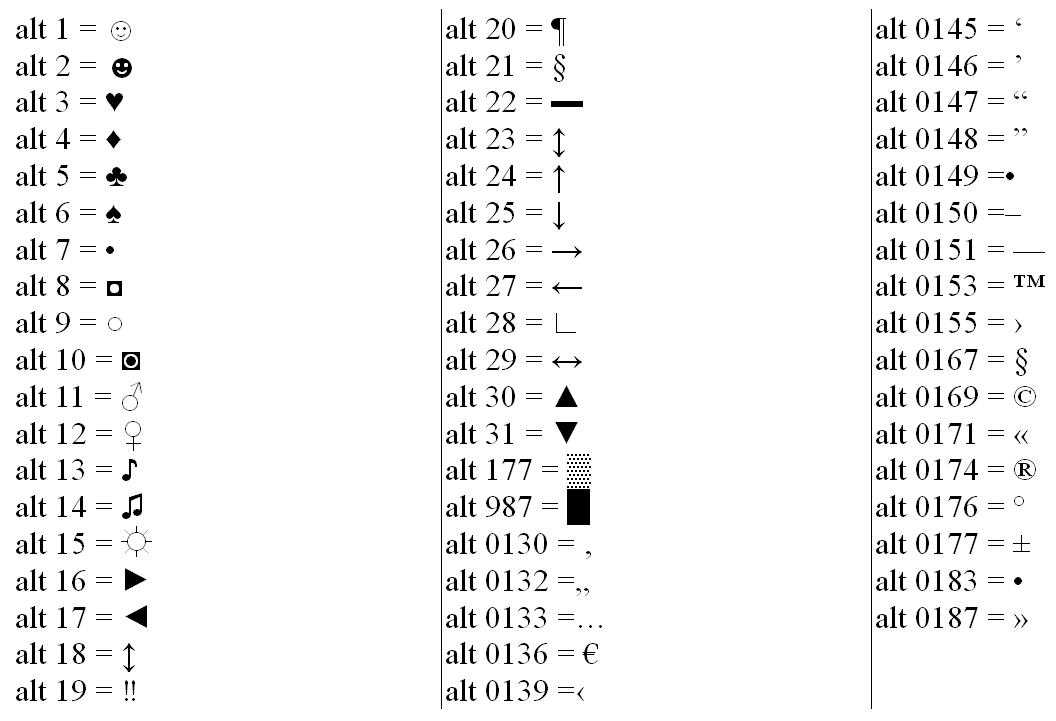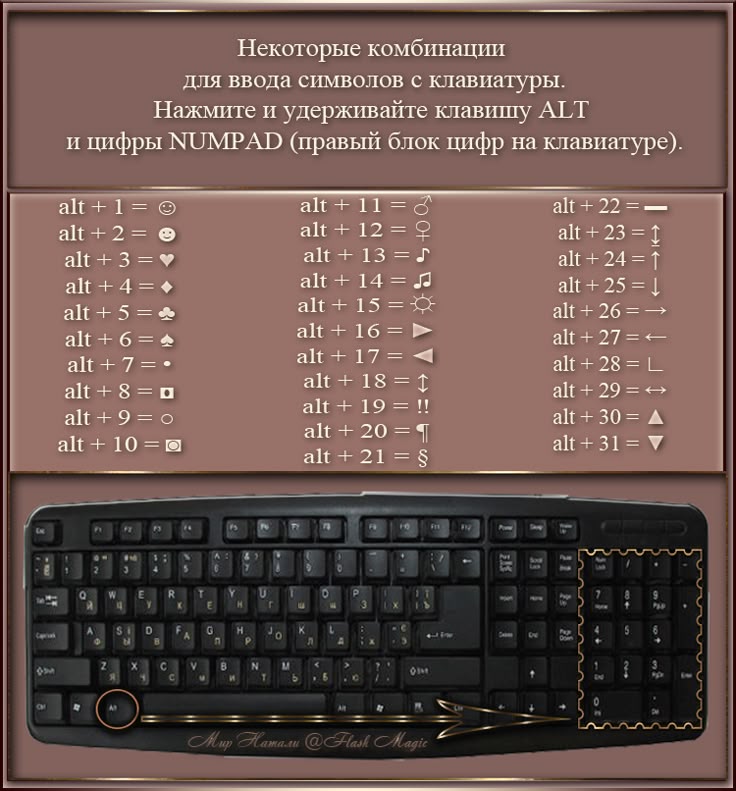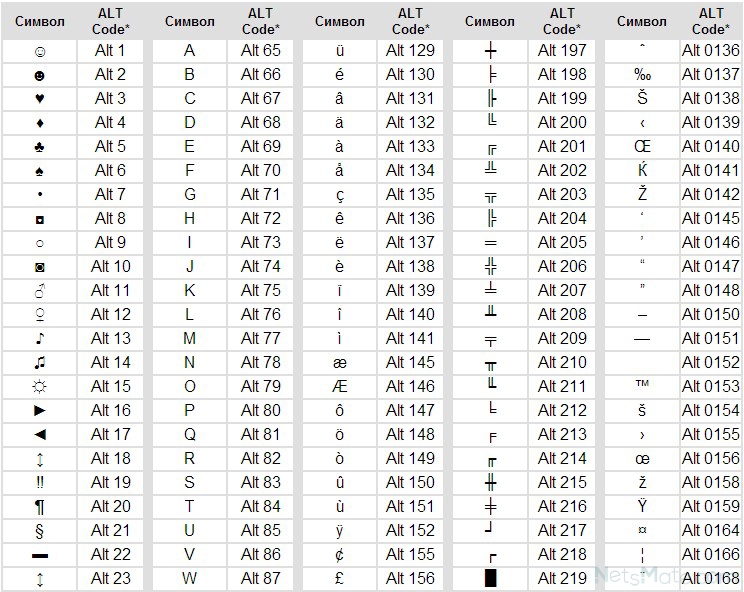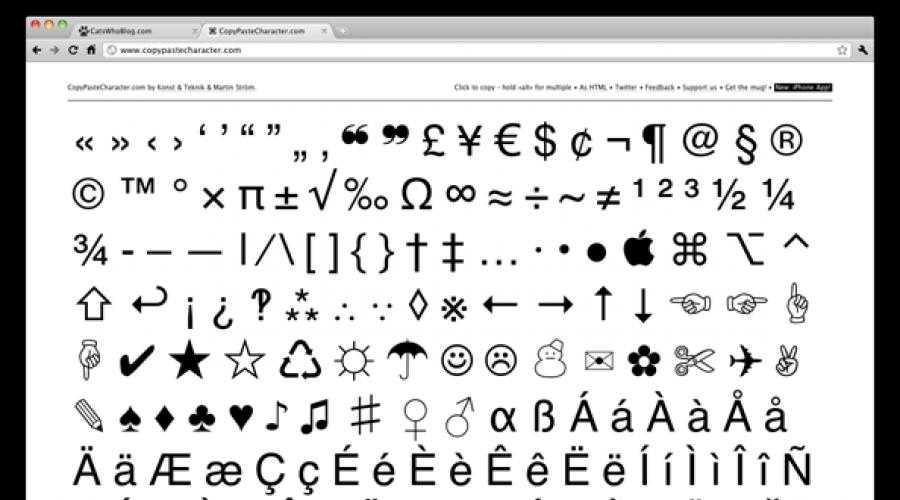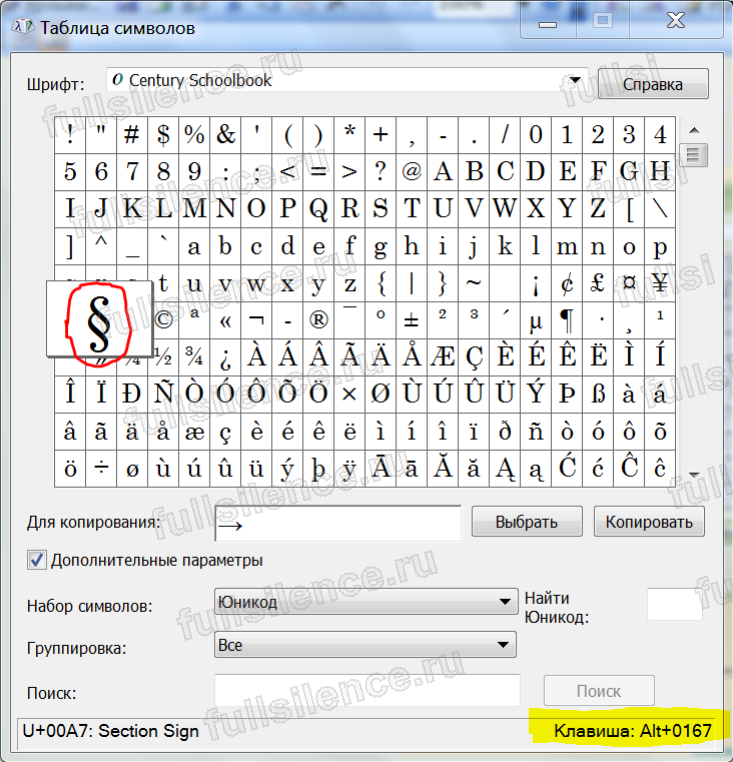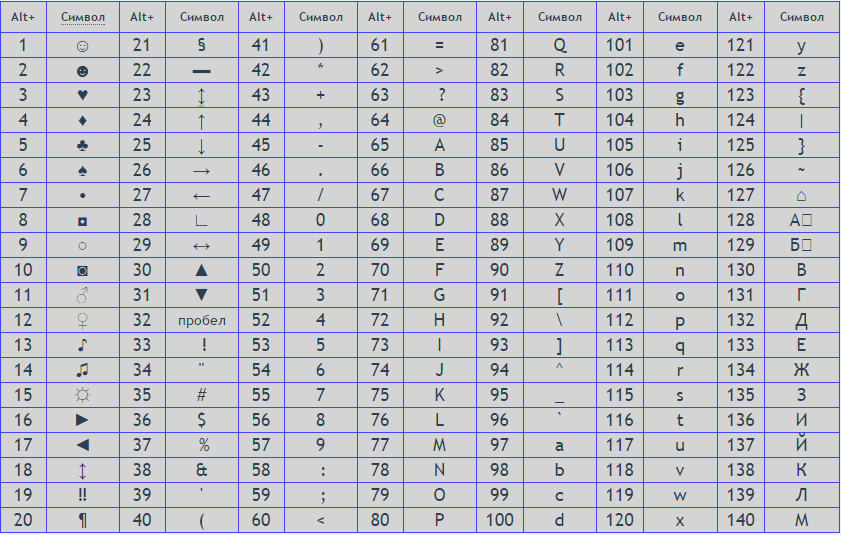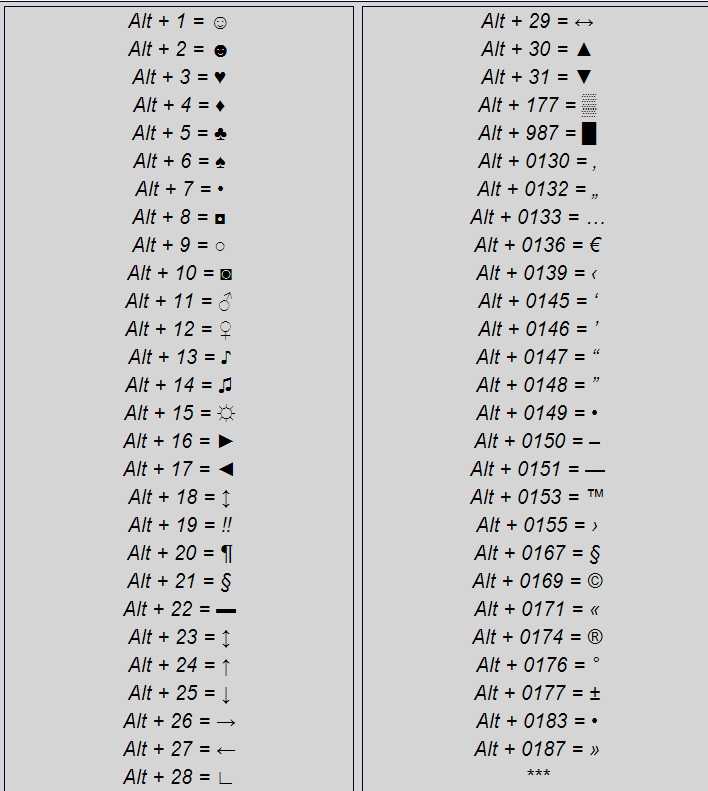
Несколько советов, как написать красивыми буквами слово
Всем известно выражение о том, что красота – страшная сила. И применять ее можно по-разному. В данной статье поговорим о том, как научиться красиво писать слова. Что для этого нужно знать и уметь?
О вариантах
В современном мире нужно уметь не только красиво писать собственной рукой на бумаге, но и интересно преподнести текст в социальных сетях, личном блоге и т. д. Сегодня это весьма важно, т. к. традиционная переписка в большинстве случаев утратила свои позиции, отдав первенство общению при помощи средств интернета.
Рукописный текст: история
В первую очередь все же следует разобраться, как написать красивыми буквами текст вручную. Интересным для многих покажется небольшой экскурс в историю. Как бы это странно ни прозвучало, но развитию письма (именно красивого, каллиграфического) посодействовала Библия. Произошло это примерно в 8-9-м веке, когда монахи Ирландии и Шотландии начали создавать иллюминированные Библии, считающиеся сегодня верхом письменного искусства. Для этого набирались священнослужители, которые обучались красивому ровному письму. И процесс этот, нужно сказать, не так уж быстр: для качественного обучения требовалось много времени и сил.
О каллиграфии
Искусство красиво писать называется каллиграфией. С греческого языка данный термин переводится как «красивый почерк». Интересным окажется и тот факт, что каллиграфия сегодня – это одно из течений в изобразительном искусстве. Большинство мастеров красивого рукописного текста свое умение определяют как оформление надписей в гармоничной, искусной и экспрессивной манере. То есть это не просто красиво написанный текст, но и грамотно и со вкусом вписанный в общую картину.
Что нужно знать?
Итак, что следует предпринять, если хочется разобраться в том, как написать красивыми буквами слово? В первую очередь важно хорошенько проанализировать свой почерк. Рекомендуется предварительно выбрать определенную манеру письма, которая подойдет конкретному человеку в зависимости от того, как он переносит текст на бумагу. На что нужно обратить внимание?
- На то, какие буквы получается украшать автоматически (завитки, дополнительные полоски).
- На наклон почерка.
- На ширину между буквами в одном слове.
В зависимости от этого можно продумать новый, украшенный стиль своего письма.
Что нужно иметь?
Итак, разбираемся далее, как написать красивыми буквами определенный текст. Для этого требуется запастись определенными вспомогательными средствами:
- Пишущим предметом. Это может быть ручка, карандаш, фломастер – не столь важно. Главное, чтобы предмет был удобен для пишущего. Прежде чем приступать к столь важному делу, нужно сделать несколько росчерков на бумаге. Это поможет убедиться в правильности выбора пишущего предмета.
- Самой бумагой. Она должна быть подходящей. Так, на лоснящемся листе маркер или фломастер рискует размазаться, а карандаш и вовсе откажется писать. Это нужно учитывать.
Правила красивого написания
Изучаем далее материал, который подскажет, как написать красивыми буквами нужный текст. Для достижения поставленной цели нужно соблюсти несколько простых правил. Что же делать?
- Тренироваться. Чтобы текст получился ровным и красивым, нужно немного попрактиковаться. Предварительно можно попробовать несколько разных манер письма и выбрать ту, которая больше всего понравилась.
- Не спешить. Сев за работу, человек не должен волноваться, спешить. Только в таком случае все получится красиво.
- Не бояться экспериментировать. Если сердце подсказывает сделать в определенном месте завиток, так и нужно поступить. Это просто небольшие подсказки подсознания, которые лучше не игнорировать.
- Научиться соединять линии. Красивый прописной почерк – это верх искусства.
- Знать разные стили письма. Для этого можно посмотреть различные шаблоны, изучить каллиграфию как элемент изобразительного искусства.
И еще несколько довольно простых и всем известных правил, которые подсказывают, как красиво написать буквы: правильно сидеть, напрягать нужные для письма мышцы, правильно поворачивать бумагу в процессе оформления текста.